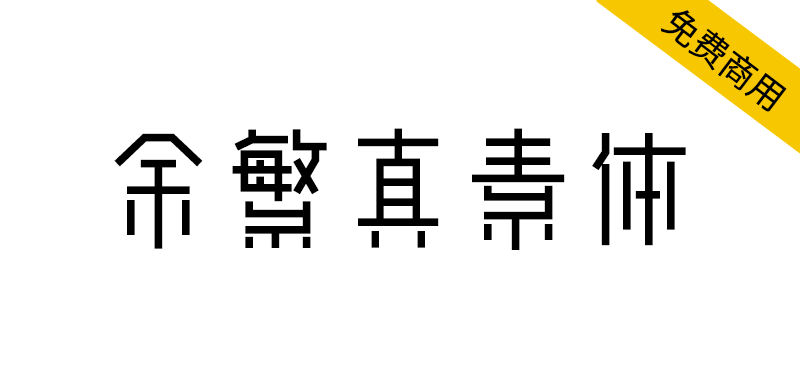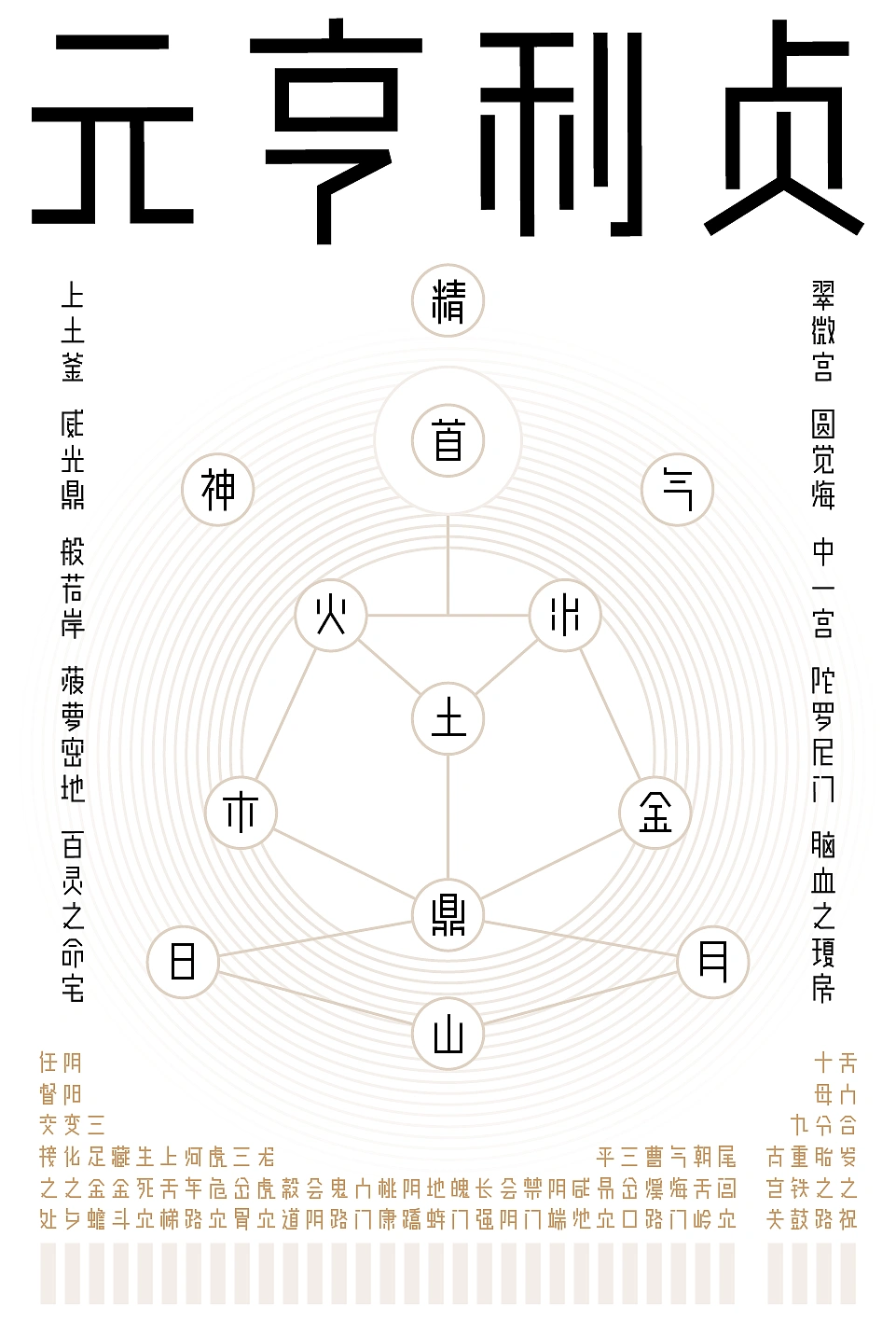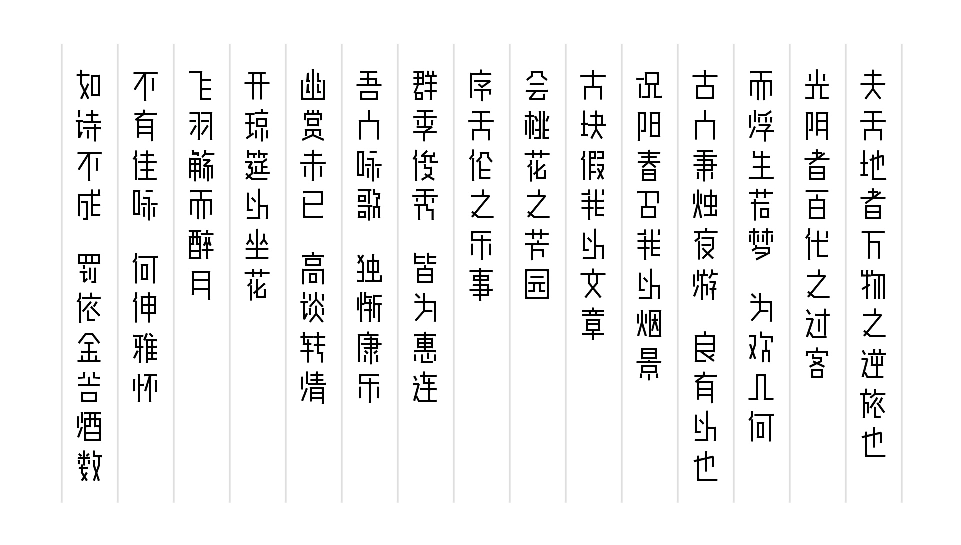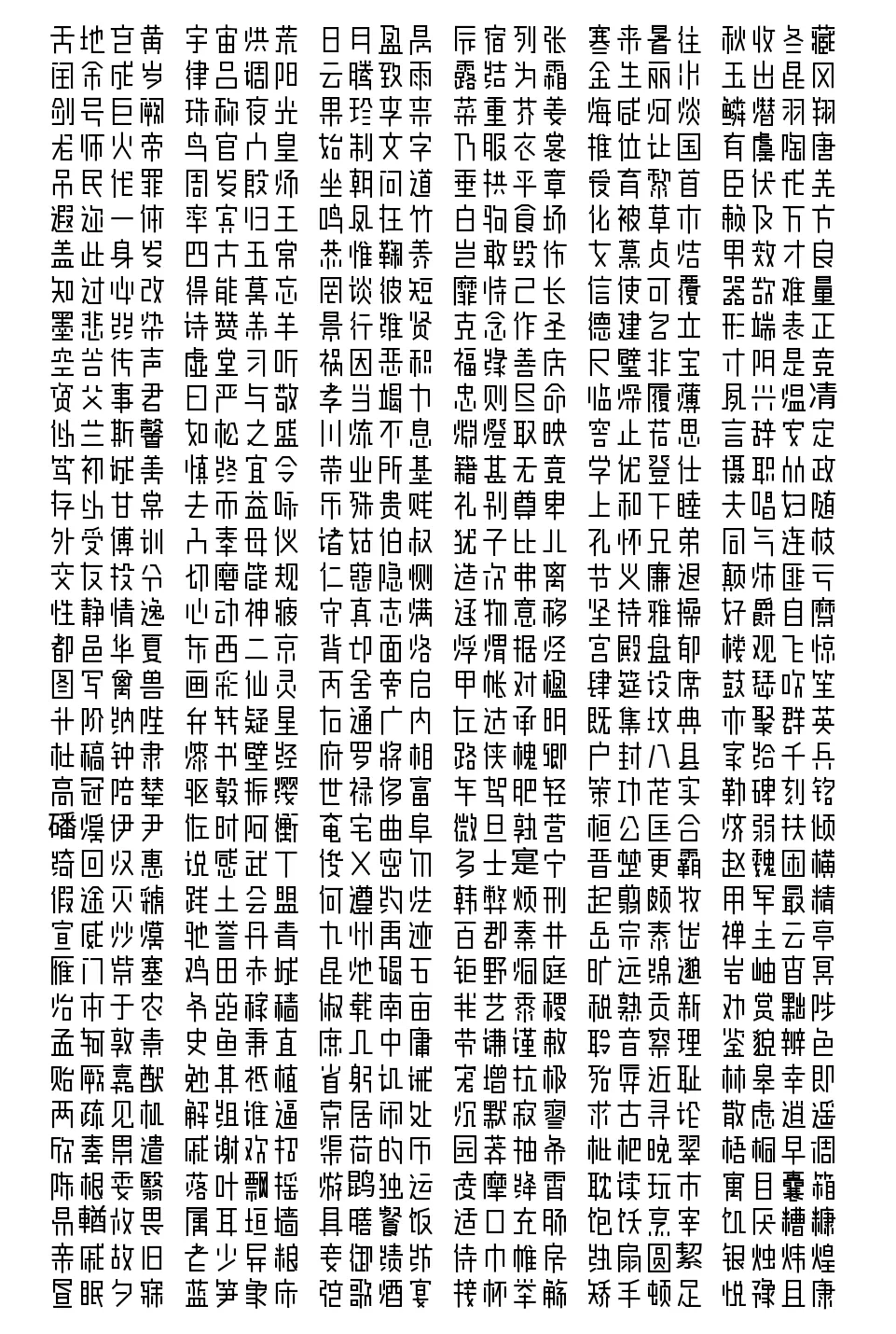
上次说到要体系化字体的视觉平衡,花了将近四个月的时间才搞定。
现理论对于正字类字体还稍显不足,但对简单创意类字体是手拿把掐。
这个版本的真素体完全重制花了两星期,对于把一个点子拓展成一个中文字体而言,这样的时间开销勉强算是可以接受了。
写得跟数学书一样的字形平衡理论估计在站酷没几人想看,单贴点图看看具体效果哈。